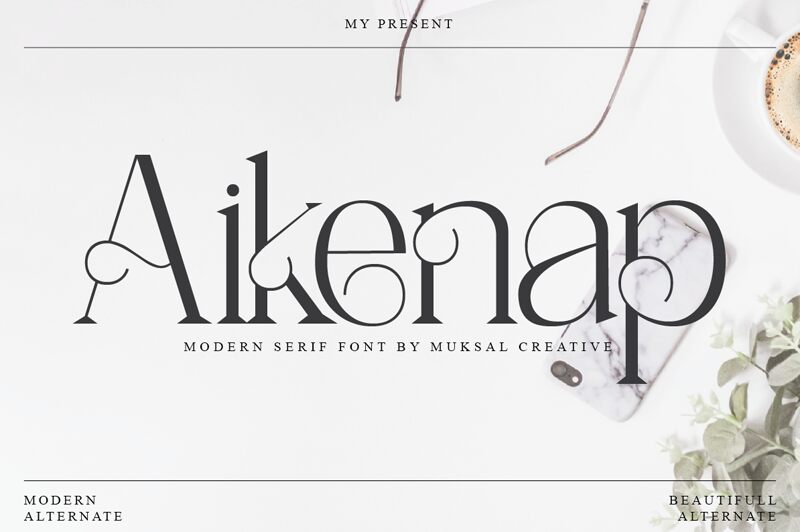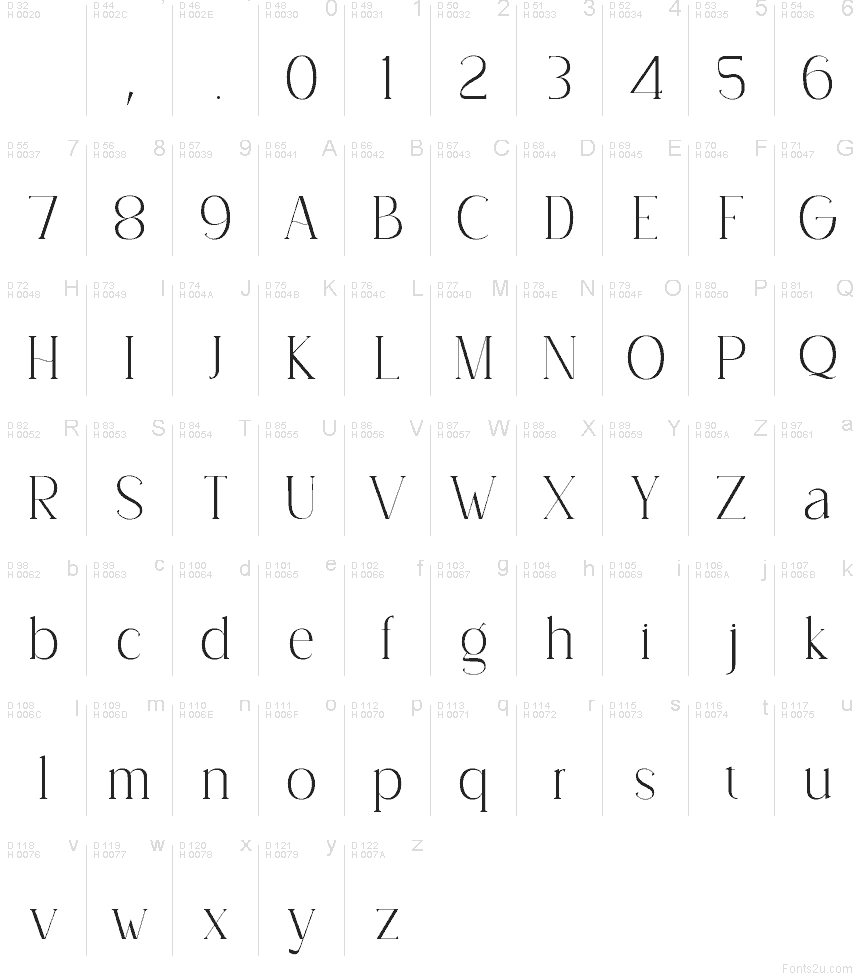
Aikenap Regular
Aikenap, bezplatné pätkové písmo od Alkenap (Muksal Creative), využíva vysoký kontrast, ktorý písmenám dodáva elegantný a módny vzhľad. Veľmi tenké spoje a vlasové linky mu dodávajú vzdušnosť, zatiaľ čo ostré detaily pätiek a jemne zvlnený priečny ťah prinášajú nečakaný prvok, ktorý sa vymyká čisto klasickému štýlu.
Táto kombinácia robí z Aikenap prirodzenú voľbu pre branding butikov, titulky v časopisoch, kozmetické obaly, svadobné tlačoviny či štýlovú grafiku na sociálne siete. Písmo dokáže vylepšiť aj logá a krátke citáty, kde jeho prepracované obrysy a jemná vnútorná dynamika ponúkajú viac než obyčajné pätkové písmo.